ฟ้อนต์ฟรีนักออกแบบทุกคนล้วนชอบยิ่งถ้าเป็นฟ้อนต์ไทยฟรีด้วยแล้วบอกได้เลยว่านักออกแบบทุกคนยิ่งชอบเข้าไปใหญ่ แต่ๆนักออกแบบส่วนมากจะนิยมใช้ฟ้อนต์ตัวไหนกันละ
เมื่อไม่นานก็นี้ก็ได้นั่งคิดว่าฟ้อนต์ไทยที่ฟรีๆมีเยอะมาก แต่ๆ นักออกแบบส่วนมากใช้ฟ้อนต์ตัวไหนกันละ เป็นคำถามที่ค่อนข้างคาใจมานานเพราะโดยส่วนตัวก็ใช้อยู่ไม่กี่ชนิดเท่านั้นจึงเกิดไอเดียถามแฟนเพจ GRAPPIK ดีกว่าว่า ฟ้อนไทยฟรี ตัวไหนที่นิยมใช้กันมากที่สุด
ฟ้อนต์ไทยฟรี ตัวไหนใช้กันบ่อยที่สุด
ผ่านไป 2 วันในที่สุดก็ได้ข้อสรุปแม้จะไม่เป็นเอกฉันท์มากนักแต่ก็ทำให้เรารู้ได้แล้วว่า ฟ้อนต์ไทยฟรี ที่นิยมใช้กันมากที่ตัวไหนกันบ้าง พร้อมแล้วจัดไป
1. Supermarket มาแรงมากหลายคนให้เป็นเสียงเดียวกันว่าเจ๋ง
ซูเปอร์มาร์เก็ต คือฟ้อนต์ไทยอีก 1 ตัวที่คนไทยนิยมใช้กันมากเพราะอ่านงายฟ้อนไม่หนาไม่บางจนเกินไป ใครชอบตามไปโหลดกันได้เลยที่นี่ LINK
2. RSU หรือ ฟ้อนต์ของมหาวิทยาลัยรังสิต
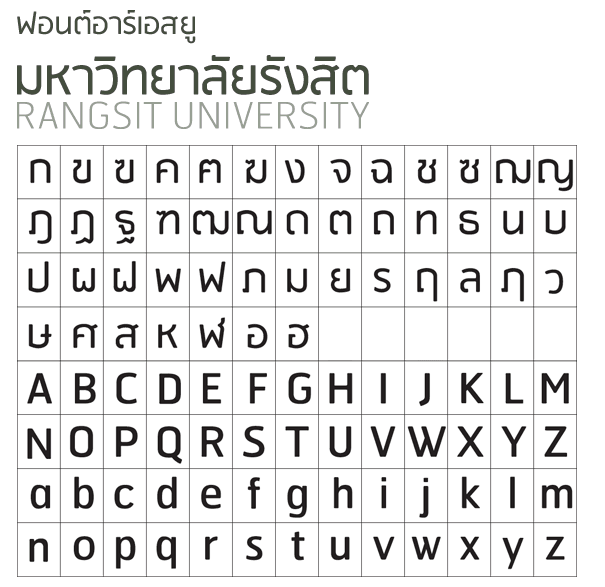
จุดเด่นของ RSU ฟ้อนต์ คือเป็นฟ้อนต์ไม่มีหัว ซึ่งดัดแปลงมาจากฟอนต์ภาษาอังกฤษชุดหนึ่ง โดยอักษรภาษาไทยที่ไม่มีหัวเกือบทุกชุดในเมืองไทย ล้วนถูกดัดแปลงมาจากอักษรภาษาอังกฤษแทบทั้งสิ้น เพราะการแปลงตัวอักษรภาษาอังกฤษให้กลายเป็นภาษาไทยจะช่วยให้มีความทันสมัย เมื่อได้ชุดอักษรภาษาไทยแล้วจึงทำาชุดอักษรภาษาอังกฤษให้สอดคล้องกัน
ฟ้อนต์ RSU เป็นอีกหนึ่งฟ้อนต์ที่ได้รับความนิยมในการนำไปใช้งานเยอะมาก โดยที่เป็นฟ้อนต์ที่ดูทันสมัยและยังสามารถใช้ได้กับงานทุกประเภทจึ่งไม่แปลกเลยที่ฟ้อนต์นี้เป็นที่นิยมมาก LINK
3. Quark : ควาร์ก
อีกหลายเสียงยกให้ Quark เป็นฟ้อนต์ไทยฟรีที่นิยมอีก 1 ตัว แต่ทั้งนี้ทั้งนั้น ฟ้อนต์ Quark ทั้งชุดมี 6 น้ำหนัก แต่เวอร์ชันสามารถใช้ฟรีได้นั้นคือ Light กับ Bold หากต้องการนำไปใช้งานให้ครบถ้วนสมบูรณ์ทั้ง 6 น้ำหนัก สามารถซื้อได้ที่นี่ครับ Typomancer หรืออยากจะโหลดไปใช้ฟรีแค่ตัว Light กับ Bold ก็โหลดกันได้ที่นี่เลย LINK
4. Sukhumvit Set
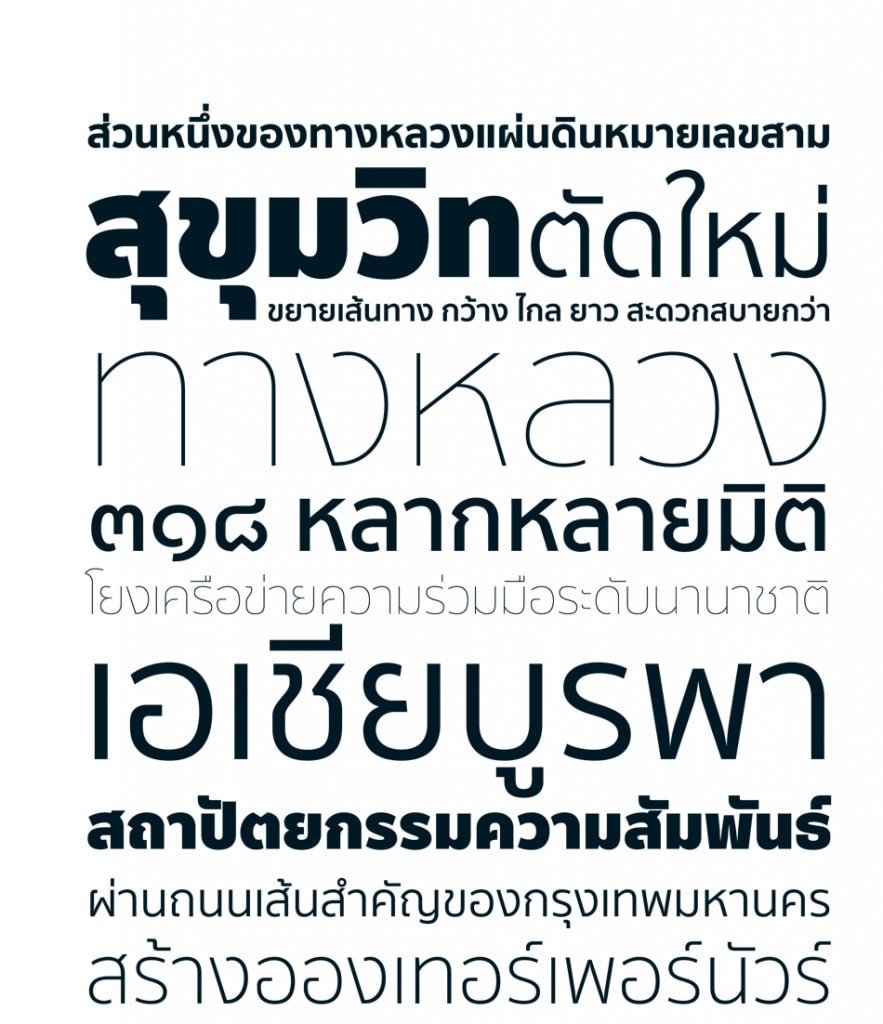
Sukhumvit Set ก็เป็นอีกหนึ่งฟ้อนต์ที่นิยมใช้แต่ๆๆๆๆจะฟรีก็ต่อเมื่อใช้ระบบปฏิบัติการของ Mac เท่านั้น เพราะฟ้อนต์ Sukhumvit Set นั้นจะติดมากับระบบปฏิบัติการ OS X Yosemite เลยครับ
5. TH Sarabun New
ฟ้อนต์ไทยฟรีที่ส่วนมากนำไปใช้ในส่วนของเนื้อหาเพราะเป็นฟ้อนต์ที่มีหัวและอ่านง่ายถูกจริตคนไทยเป็นที่สุด เพราะด้วยคนไทยเคยชินกับฟ้อนต์ที่มีหัวจากหนังสือพิมพ์และนิตยสารต่างๆ จึงไม่แปลกใจที่ฟ้อนต์ตัวนี้จะเป็นที่นิยมนำมาใช้ในส่วนของเนื้อหากันมากที่สุด โหลดกันได้ที่นี่เลย LINK
6. เอกมัย มาตรฐาน (Ekkamai Standard)
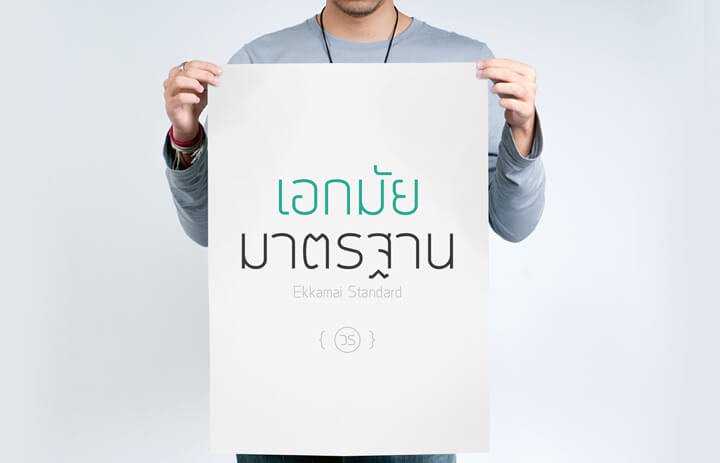
เป็นฟ้อนต์แบบไม่มีเชิงที่เรียบง่ายและดูดี สามารถนำไปประกอบงานออกแบบได้หลากหลายสไตล์ โดยฟ้อนต์เอกมัยนั้นสามารถใช้งานได้ฟรีกับงานทุกประเภท